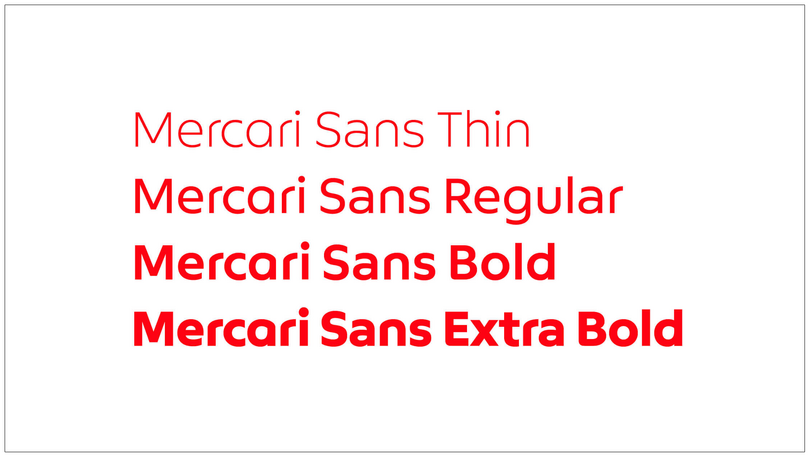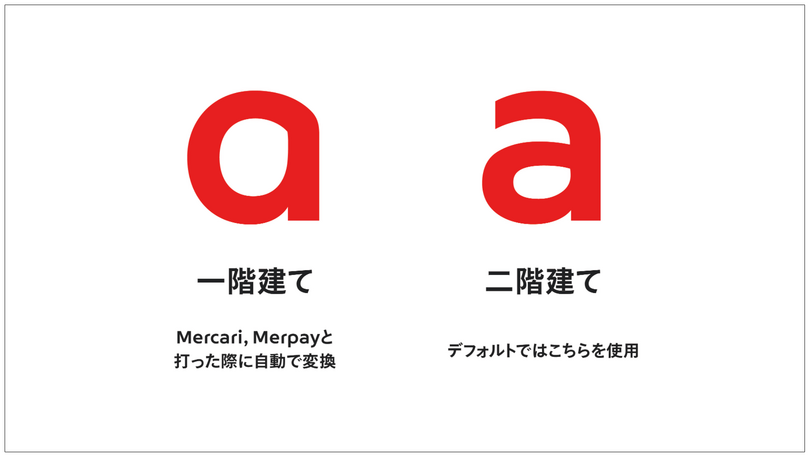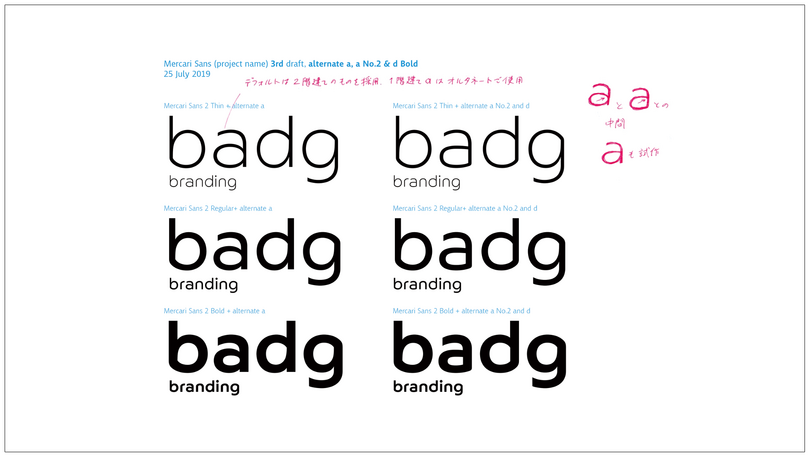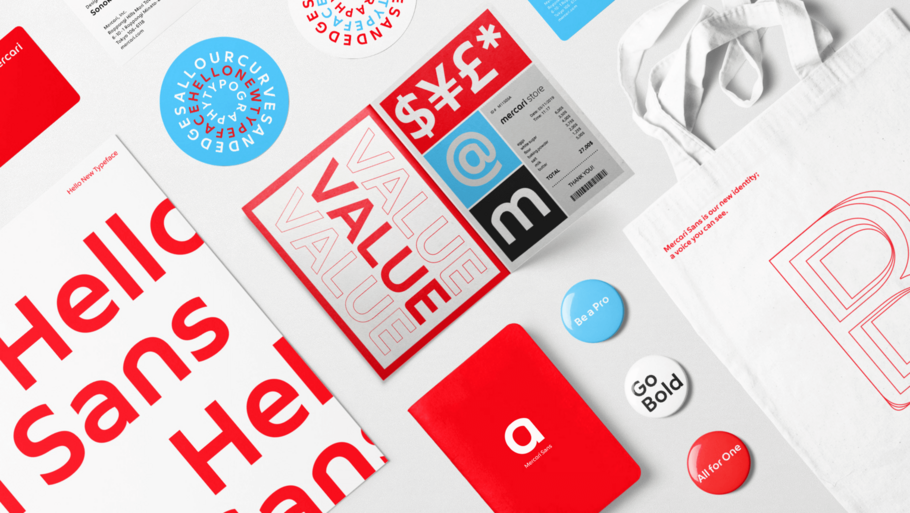
メルカリのコーポレートフォント
社内外に向けた総合的なブランド戦略とは
Monotypeは、フリマアプリ「メルカリ」のサービスを運営する株式会社メルカリのコーポレートフォントMercari Sansを制作しました。
Monotypeは、2019年10⽉、フリマアプリ「メルカリ」のサービスを運営する株式会社メルカリのコーポレートフォントMercari Sansを制作しました。
株式会社メルカリは、2019年に会社のロゴタイプを変更。オンライン、オフラインの双方で一貫 した「メルカリらしさ」を伝えていくために、目に見える“声”としての文字が重要と考え、コーポ レートフォントの制作に至りました。
コーポレートフォントの制作チームは、メルカリの新しいロゴタイプを担当したデザイン・イノ ベーション・ファームTakramのアートディレク ター弓場太郎氏、メルカリの社内デザインチーム、 Monotypeクリエイティブタイプディレクターの小林章。たづがね角ゴシックを和文書体として使用し、たづがね角ゴシックおよびメルカリのロゴタイプとあわせて使える欧文書体を新たに開発するプロジェクトが始動、Webサイト、印刷媒体、 IR 資料、広告、メルカリが展開するサービスのロゴなどで使われることを想定し、トラスト(安心、 信頼)とオープン(公平さ、親しみやすさ)が感じられるデザインを目指しました。
実際の書体制作では、デザイン案を画面で共有 しながら、オンラインミーティングを実施。求めている文字の形が見つかった時には、制作チーム 全体が「これだ!」と、どよめいた瞬間もありま した。自社ブランドについて活発な意見交換がなされ、チーム全員が共通の認識をもち意思決定をするという場があったことが今回のプロジェクトの大きな特徴でした。
「コーポレートフォントを作るプロセスによって、 企業の強みや、らしさが見つかりました。企業の中で書体を作るということ自体がパワフルな取り組みだと思います」とTakramの弓場氏は語りま す。こうして完成したMercari Sansは、メルカリのWebサイトをはじめ、ブランディングのあらゆる場面で使われています。